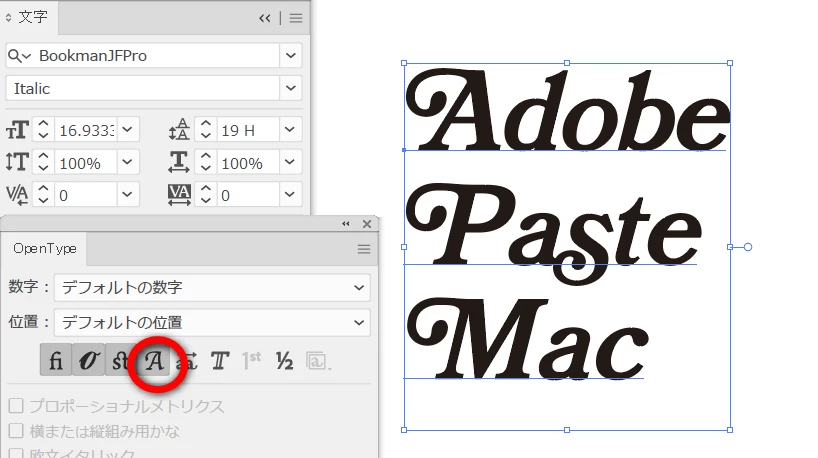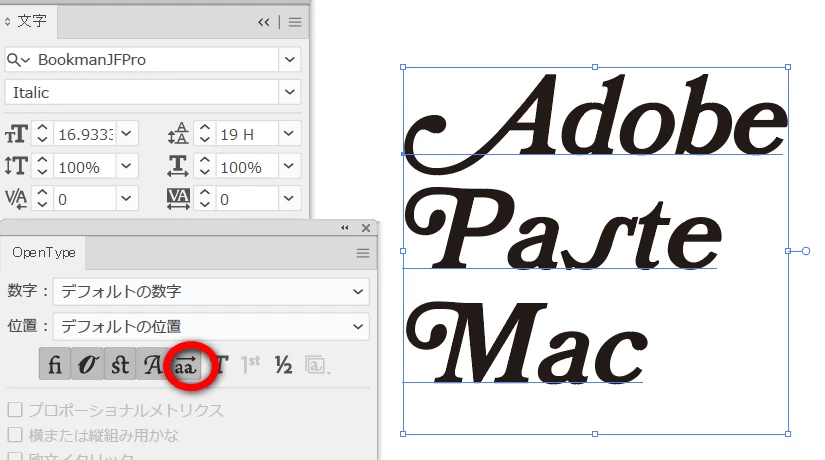
また、書体の分類としては(セリフ、サンセリフ、飾り文字など)いずれになるのでしょうか。。。
AdobeFontsのビジュアルサーチを利用すると良いでしょう。
恥かしながら、スワッシュ字形(swash)の存在はまったく初耳でした。
書体の分類としては、セリフのイタリック体でスワッシュ字形(swash)です。
Illustrator等で使用する場合はスワッシュ字形のチェックを入れたりバリエーションのチェックを入れたりしないと表示できないので、見本としては載っていないケースがほとんどです。